设计前的思考
文字是一种记录与传达语言的符号,是人类文明进步的重要标志。随着图形化时代的来临,文字与图形的关系在设计领域起着举足轻重的作用。当练习字体设计时,找有代表性的字体来做,练习有代表性的字体不但可以激发你的创意,还可以提高你的思维能力。文字经过艺术化设计后,可以让文字形象变得情景化、视觉化、强化语言效果,对提升页面设计品质 和视觉 v表现力发挥了极大性的作用。
什么是代表性的字体?
如:时间你就会联想到钟表 ,对话你就会联想到电话 ,爱情你会想到心 想到这些有代表性的字时,谨记不能把钟表等图形直接放在字体里,这样就没有设计的意义了,要巧妙的把图形和字体本身去结合。
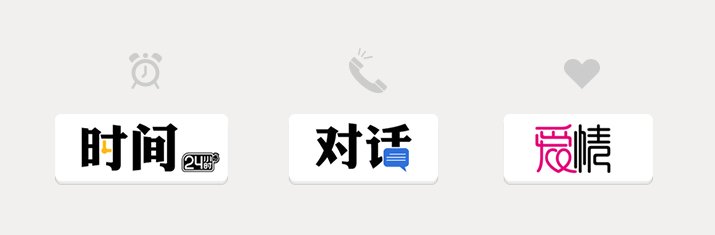
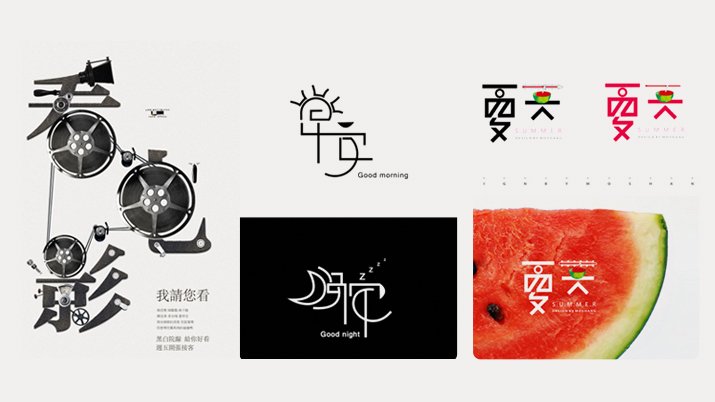
字形风格
经过艺术化设计以后,可使文字形象变得情境化、视觉化,强化了语言效果,成为更具有某种特质和倾向性的视觉符号。字体设计最基本的准则,在追求字体变化的同时要便于识别。 字形变化中特点: (硬)—– 力道、坚实、冲击、厚重、硬朗、猛烈 …… 这类字体气势突出,视觉冲击力明显,个性张扬有力,节奏分明,可以用于变现强烈的信心和勇气,表现凝聚力和号召力,给人视觉上的震撼。 这类字形因其字形富有张力,所以在表现刺激,冒险的情景时比较常用,如体育活动、极限运动的主题同时战争类、灾难类电影海报中,这类字形也比较常见。
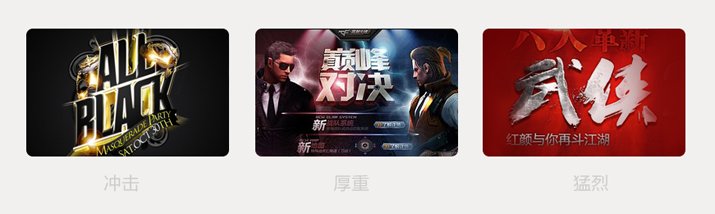
字体创意设计虽然比较自由,但应保持字与字之间的统一性。一组字体设计中,应保持一种统一的变化规则,不然会造成杂乱感。
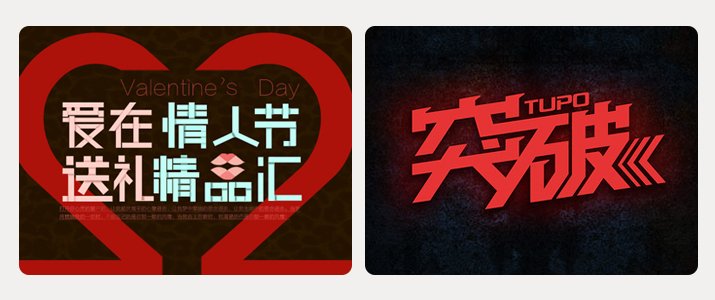
字形变化中特点: (软)—– 柔美、纤细、优雅、亲近、温和、飘逸 …… 这类字体适合表现细腻情感,如情感类设计主题、女性设计主题、公益类设计主题等等,通过柔美的曲线壁画,可以让自已得到更大程度的展现,通过视觉感觉,形成人与字的情感共鸣,以达到最佳效果。
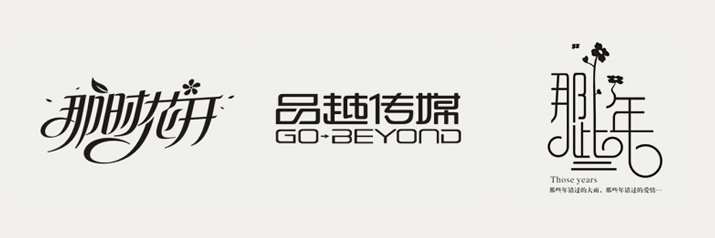
字形变化中特点: (旧)—– 严肃、端正、正式、中性、规t矩、传统、古朴、怀旧…… 这类字形在品牌类字体中比较常见,给人以饱满充实的信赖感和说服力,保持规则的字体外形,在字体内部进行适度的笔画修整,在严谨中求突破,在规矩中求创新。
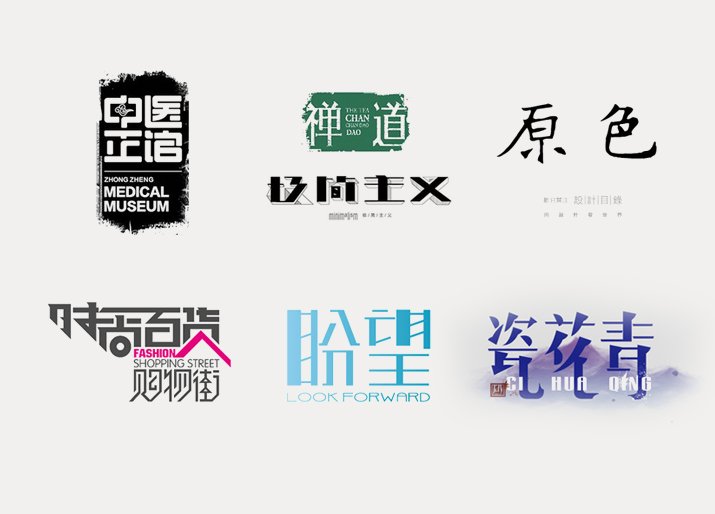
图例
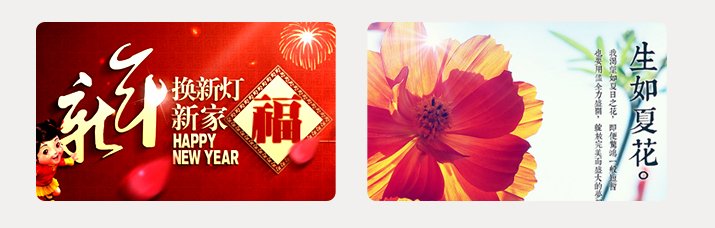
字体变形的几种方法与技巧
代替 共用 叠加 尖角 断指 错落连接 方正 横细竖粗 字体连接 随意手写 曲线 图型 拉伸
替代法
替换法是在统一形态的文字元素加入另类不同的图形元素或文字元素。 其本质是根据文字的内容意思,用某一形象替代字体的某个部分或某一笔画,这些形象或写实或夸张。将文字的局部替换,是文字的内涵外露,在形象和感官上都增加了一定的艺术感染力。
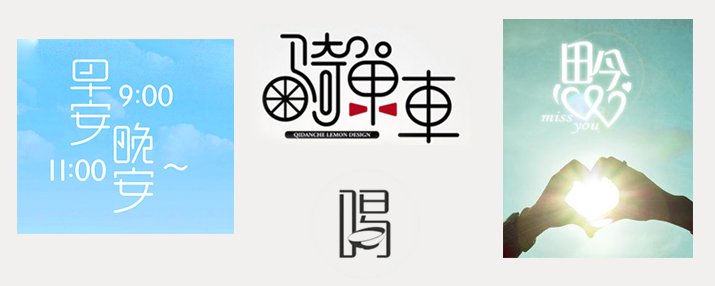
尖角法
把字的角变成直尖,弯尖,斜尖,卷尖; 可以是竖的角可以是横的角,这样文字看起来会比较硬朗
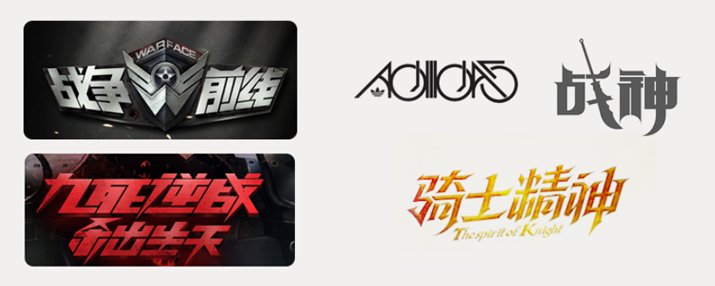
断指法
把一些封合包围的字,适当的断开一口出来 , 或把左边断一截,或右边去一截, 重点:要在能识别的情况下适当断肢,从而反射他的与众不同的特点来。
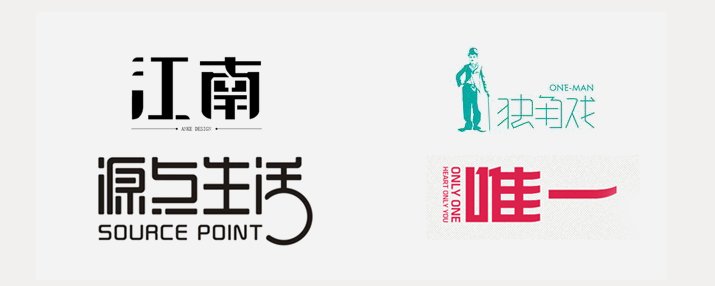
错落摆放法
把左右改为左上左下,上下排,或斜排就是一边高一边低,让文字错落有致排列
方方正正法
把所有字的弯全改成横平竖直,四四方方的。 本身的特点是简洁鲜明的,便于设计,对熟悉字体结构有很好的帮助。
横细竖粗法
可以说是代替法的一种,把竖或横线或折换成其他相反交替而成。 笔画简化,在字体中加入个人情感和生活,可以准确的创意方向,设计出合适自己的字体
随意手写
原笔迹的手写体总给人也亲切的感觉,《那些年》追忆的正是校园时期的青葱岁月,手写字每一笔都不可复制,每一划都触景生情。
字体变形中应该规避的问题
可阅读性 识别能力 肩胛结构 应用环境
在字体设计中,很多设计项目都需要严谨仔细,设计师必须去认真的推敲尝试每一个笔画的变化方式,去选择最合适的表现方法,只有如此才能使得每一个笔画都契合这个字体,符合整组字的空间规则。
图形绘制软件,可以帮我们完成各种圆角、对称、倾斜、等距分布、交差减去等任务。
还有就是可以把字体轮廓化描边,快速运用基础字体来变形。
尽可能地保证文字的可阅读性,终归是商业设计,要考虑到大部人的文化背景和图形识别能力。
完成字体变形,可以分几步来进入细节的修饰。
这个时候可以参考下类似的优秀字体的间架结构,调节好每个字的笔划分布和重心均衡。
在选定字体的风格趋势后,给字体做相应的视觉梳理。
例如:字与字的间距,笔划之间的间距、整体字形的倾斜角度特殊地方做圆角处理等等。
让整个字体有一个贯穿始终的规则在里头。
掌握字体的肩胛结构,避免大小不一、分布不均、笔画不均等问题。
统一应用笔划、倾斜等规则。鉴于字体形态的趣味性,加入了图形元素来丰富字体本身。
同时兼具不同尺寸下的显示效果,做笔划的删减和间距调整。
设计过程中应该规避尽可能地保证文字的可阅读性。
商业设计,要考虑到大部人的文化背景和图形识别能力。
还有文字变型的过程中应用的环境。